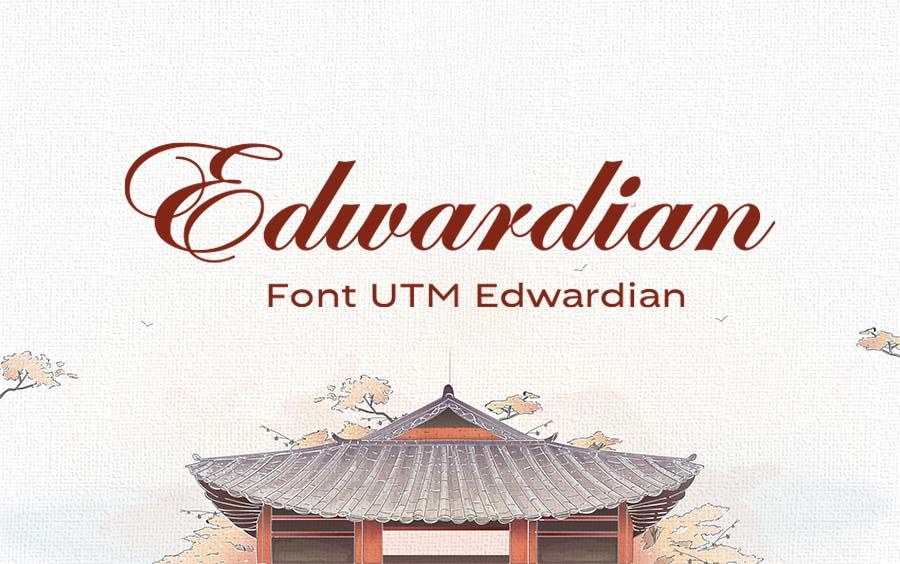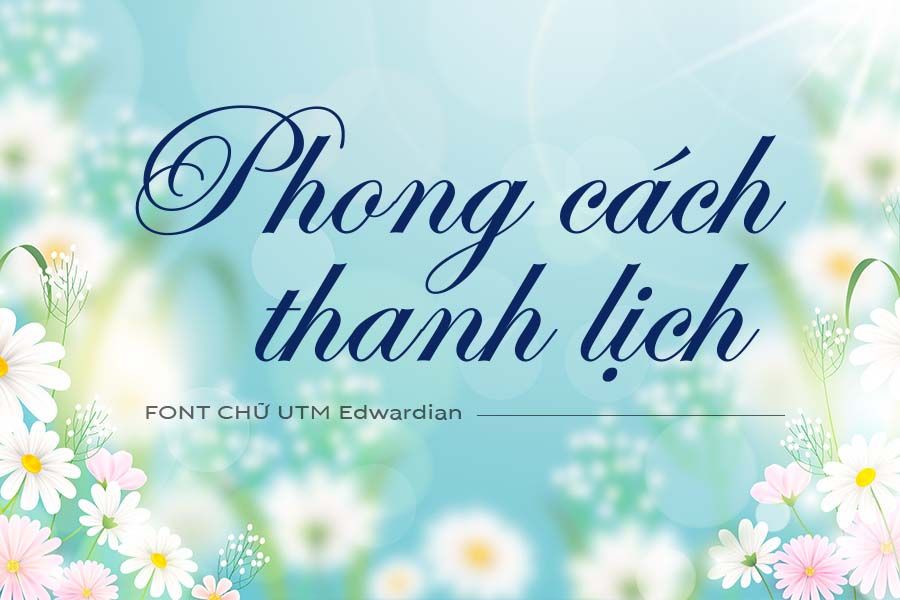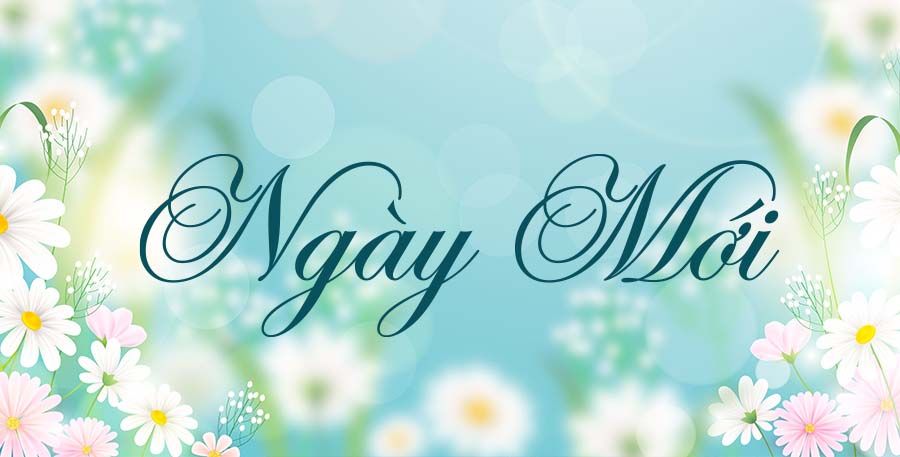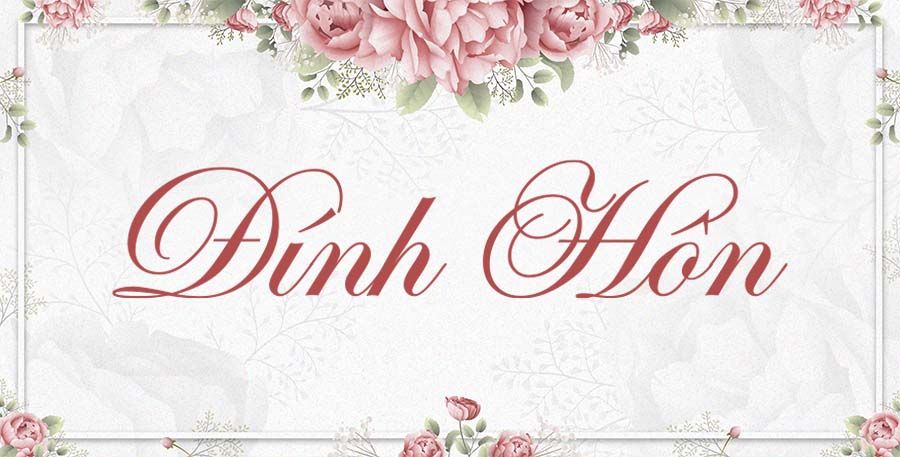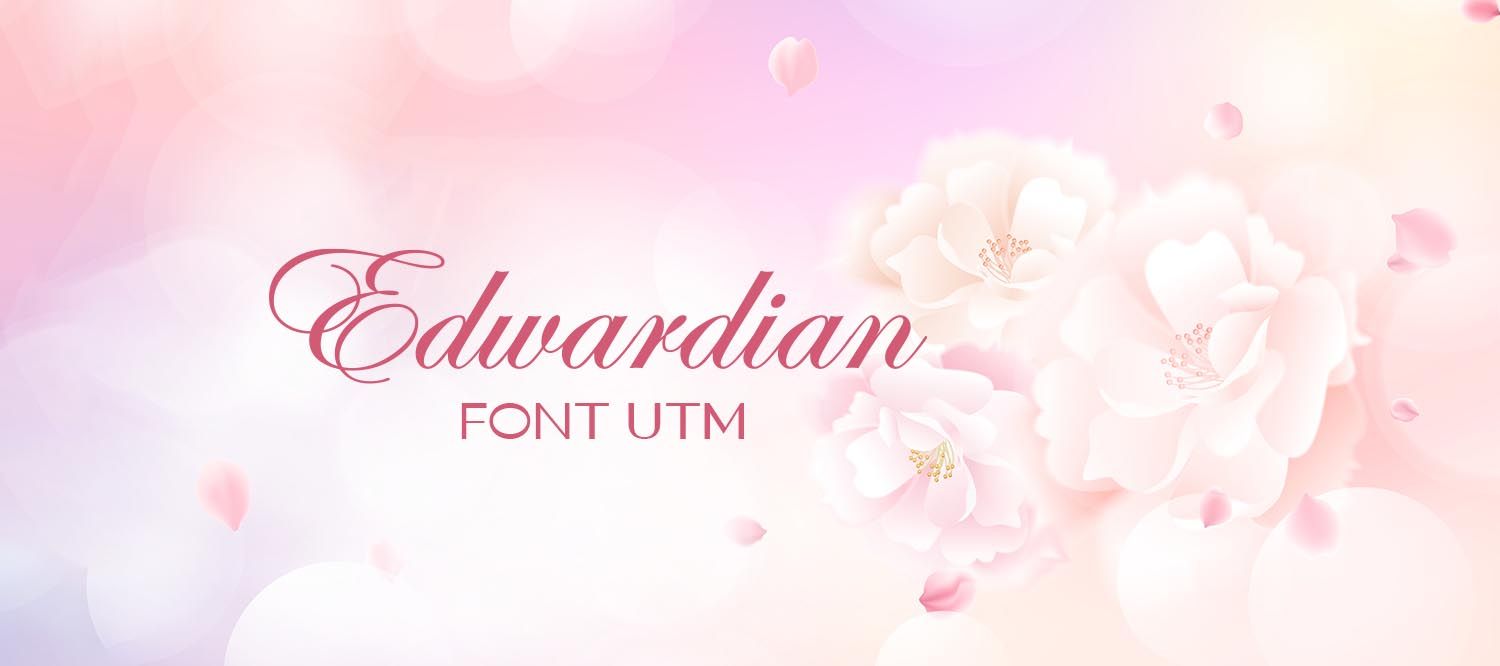
Font chữ đóng vai trò vô cùng quan trọng trong việc thể hiện tinh thần, cảm xúc và cá tính của một thiết kế. Trong số hàng ngàn font chữ hiện nay, những kiểu font viết tay cổ điển luôn mang đến vẻ đẹp thanh lịch, lãng mạn và đầy cảm xúc. Một trong những đại diện tiêu biểu cho phong cách này chính là font UTM Edwardian – bộ font chữ Việt hóa nổi bật với đường nét bay bổng, mềm mại và tinh tế. Trong bài viết này, hãy cùng chúng tôi khám phá trọn vẹn về kiểu chữ UTM Edwardian: nguồn gốc, phong cách thiết kế, ứng dụng thực tiễn và cách tải về dễ dàng.
UTM Edwardian là phiên bản Việt hóa của font gốc Edwardian Script ITC, được thiết kế bởi nhà thiết kế huyền thoại Edward Benguiat – người đứng sau nhiều kiểu chữ kinh điển trong lịch sử typography.
Với mục tiêu giữ lại trọn vẹn tinh thần quý tộc, thanh lịch của bản gốc, nhóm Urban Type Management (UTM) đã Việt hóa font này một cách khéo léo, thêm vào hệ thống ký tự tiếng Việt đầy đủ mà không làm mất đi nét mềm mại vốn có của từng chữ cái. Đây chính là điểm đặc biệt khiến UTM Edwardian trở thành một font chữ không thể thiếu với những nhà thiết kế yêu thích phong cách cổ điển – sang trọng.
UTM Edwardian sở hữu những nét chữ mảnh mai, cong lượn và nối liền nhau giống như những dòng chữ viết tay bằng bút truyền thống. Các đường nét được thiết kế uyển chuyển, mềm mại nhưng vẫn giữ độ đều và nhịp điệu thị giác, giúp văn bản trở nên sinh động và duyên dáng.
Font có hai kiểu chính: Regular – mảnh và nhẹ, phù hợp với phần nội dung chính hoặc dòng chữ dài; và Bold – đậm hơn, lý tưởng cho tiêu đề hoặc điểm nhấn trang trí, tạo nên sự tương phản tinh tế trong cùng một thiết kế.
Ngay từ cái nhìn đầu tiên, font chữ này đã mang lại cảm giác cổ điển và đầy tinh tế – tựa như những bức thư tay thời kỳ Phục Hưng. Nó tạo nên một bầu không khí lãng mạn, nhẹ nhàng và tràn đầy cảm xúc, rất phù hợp cho các thiết kế mang tính hoài niệm hoặc trang trọng. Phiên bản Bold không làm mất đi sự duyên dáng vốn có mà còn tăng thêm phần mạnh mẽ, giúp nổi bật những nội dung đặc biệt trong bản thiết kế.
Không chỉ đẹp mắt, UTM Edwardian còn dễ sử dụng trong nhiều bối cảnh khác nhau. Nhờ vào hệ thống ký tự đầy đủ (bao gồm chữ hoa, chữ thường, dấu tiếng Việt và các ký tự đặc biệt), font có thể được ứng dụng linh hoạt trong nhiều loại thiết kế khác nhau: từ thiệp cưới, logo, bao bì mỹ phẩm cho đến thư mời sự kiện. Sự kết hợp giữa hai kiểu chữ Regular và Bold cũng mang lại sự đa dạng trong bố cục và trình bày, giúp thiết kế trở nên cuốn hút hơn mà vẫn giữ được tính nhất quán.
Đây là ứng dụng phổ biến nhất của UTM Edwardian. Kiểu chữ thanh lịch này cực kỳ lý tưởng để làm phần tiêu đề thiệp cưới, thư mời, hoặc lời chào trang trọng trong những sự kiện cao cấp.
Với vẻ đẹp chuẩn mực và cổ điển, font này cũng được sử dụng rộng rãi cho việc thiết kế giấy chứng nhận, bằng khen hoặc các tài liệu mang tính nghi lễ.
Các sản phẩm thủ công mỹ nghệ, đồ trang trí vintage hay sản phẩm sáng tạo cá nhân đều trở nên sang trọng và chuyên nghiệp hơn khi kết hợp với font UTM Edwardian trên bao bì hoặc nhãn mác.
Tên đầy đủ: UTM Edwardian
Font gốc: Edwardian Script ITC
Tác giả gốc: Edward Benguiat
Việt hóa bởi: Urban Type Management (UTM)
Hỗ trợ tiếng Việt: Đầy đủ ký tự có dấu
Trong vô vàn lựa chọn font chữ viết tay, UTM Edwardian nổi bật bởi sự mềm mại, đúng chuẩn và khả năng truyền cảm tốt. Đây là kiểu chữ viết tay không bị "sến" như nhiều font script khác, mà mang đến cảm giác tinh tế, nhã nhặn và chuyên nghiệp. Nếu bạn cần một font chữ để “kể chuyện” bằng cảm xúc – từ tình yêu, sự trang trọng đến nghệ thuật thủ công – thì UTM Edwardian là cái tên đáng để lựa chọn.
Font chữ UTM Edwardian là minh chứng hoàn hảo cho sự giao thoa giữa nghệ thuật viết tay cổ điển và thiết kế hiện đại. Nhờ được Việt hóa đầy đủ và giữ nguyên vẻ đẹp gốc, font này không chỉ là công cụ thiết kế – mà còn là một phần của câu chuyện bạn đang kể.